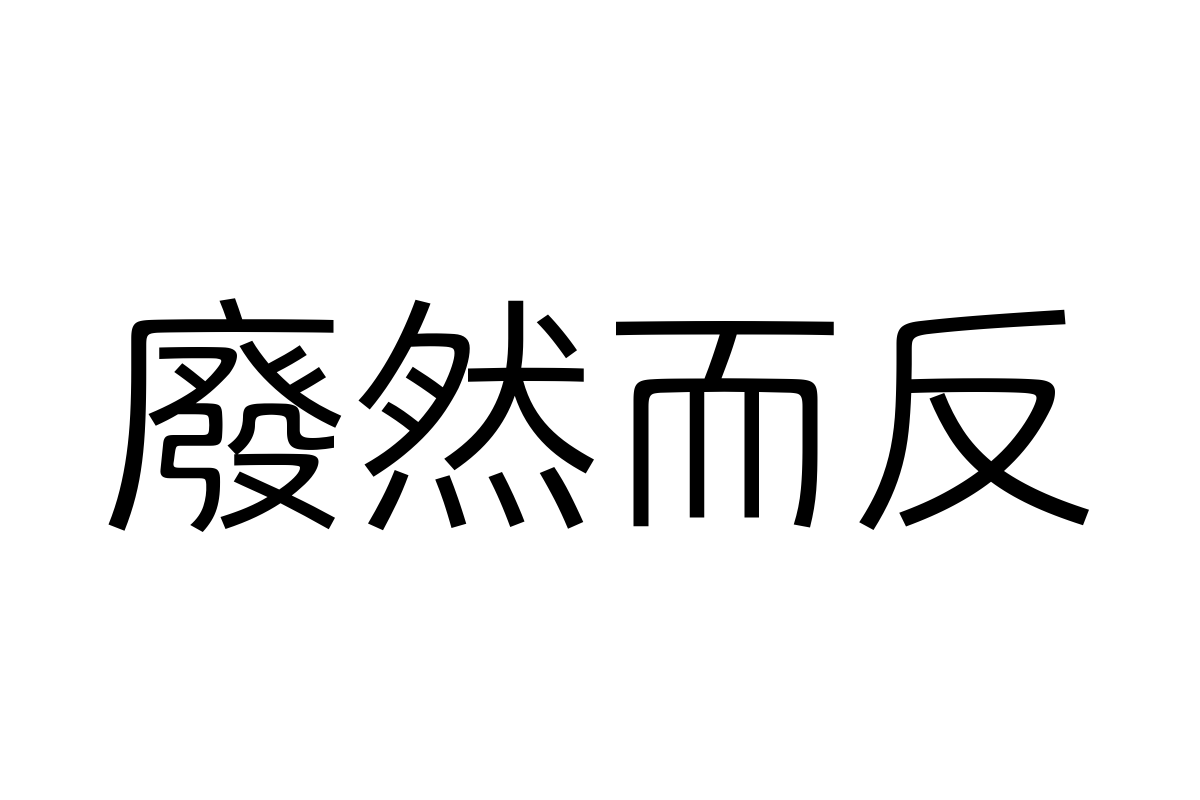
汉仪有圆45繁体字体是一种具有现代感的中文字体,其特点是笔画流畅、字形简洁大方。这种字体适合用于各种需要清晰易读的文本排版,如书籍、杂志、报纸、广告等。
汉仪有圆45繁体字体的特点如下:
1. 字形规整:汉仪有圆45繁体字体的字形结构规整,每个字符的间距和位置都经过精心设计,使得整个文本看起来更加整洁有序。
2. 笔画流畅:这种字体的笔画线条流畅自然,没有过多的装饰性元素,给人一种简洁明了的感觉。
3. 适应性强:汉仪有圆45繁体字体适用于多种印刷媒介,无论是在纸张、塑料、金属还是其他材料上都能保持良好的可读性和视觉效果。
4. 易于识别:由于字形规整,这种字体的字符容易识别,对于非专业的读者来说,阅读起来也相对容易。
总的来说,汉仪有圆45繁体字体是一款非常适合现代设计需求的中文字体,无论是在商业广告、品牌宣传还是日常办公应用中,都能展现出其独特的魅力。
汉仪有圆45繁体